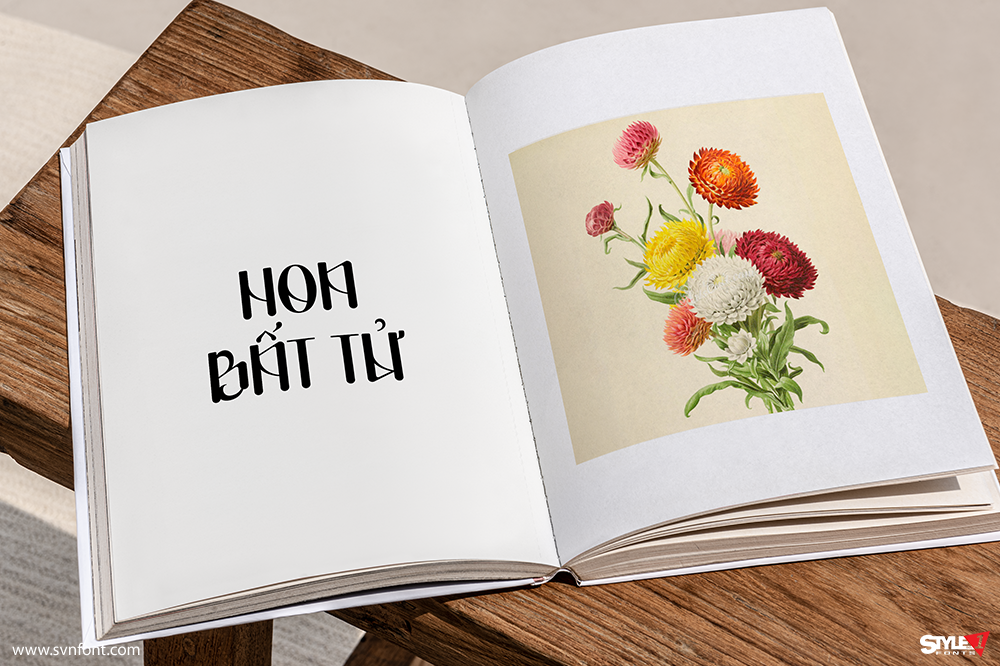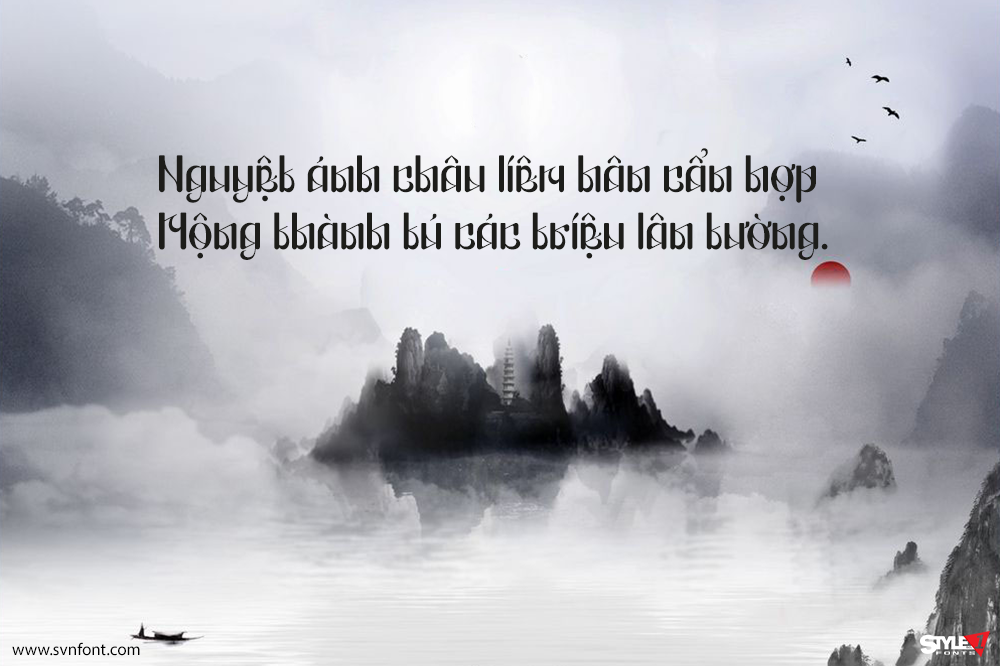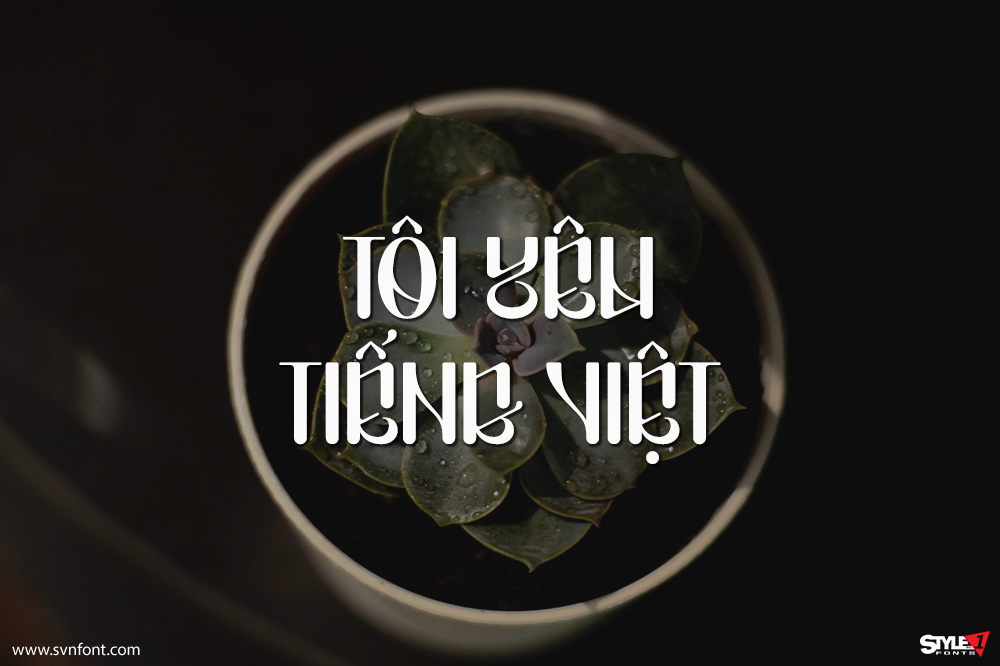
Nubya là một display typeface với độ tương phản nét rất mạnh, lấy cảm hứng từ tinh thần thư pháp và hình thái chữ Ả Rập đầy cá tính. Các nét chéo, khẩu độ khép, cùng những hình khối lặp lại tạo nên bầu không khí sống động, khó đoán và tràn đầy năng lượng, mang lại làn gió mới cho nhiều bối cảnh thiết kế.
Cấu trúc chữ của Nubya được biến đổi khỏi khuôn mẫu thông thường, nhằm tạo nên tính độc đáo và chuyển động, trong khi các yếu tố nhất quán giúp duy trì dòng chảy và nhịp điệu thị giác hài hòa.